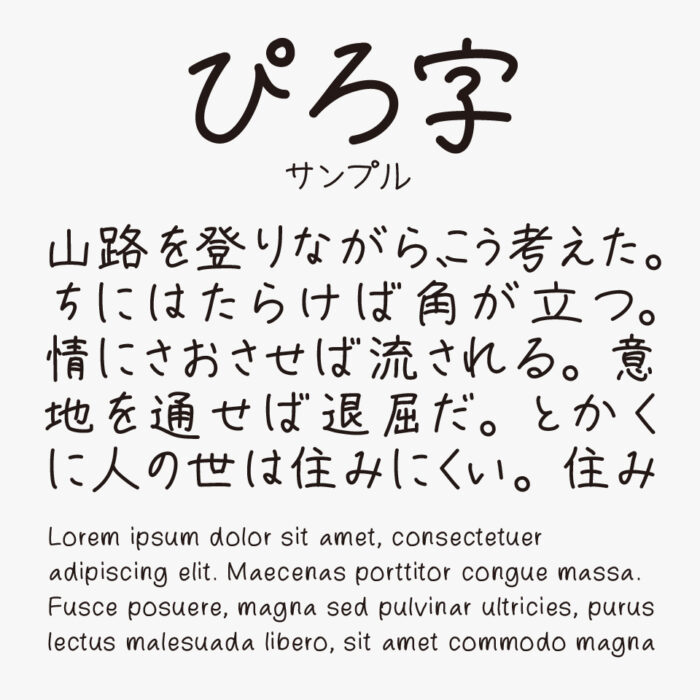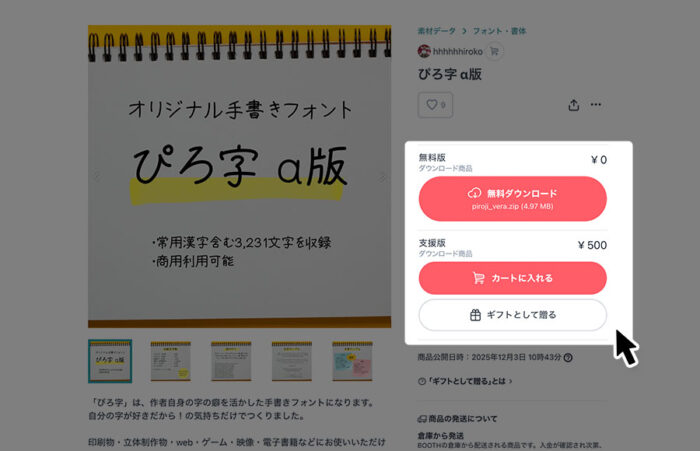
ぴろ字 α版
ぴろ字 α版は、やさしい手書き感と丸みを帯びた線が特徴の、作者はらだひろこさんの字の癖を活かした手書き風フォントです。
文字は少し丸めで、整った字ながら無垢さと安心感があり、素朴な表情をもっている手書き文字です。ナチュラルで飾らない印象を与えたいときに使いたくなる、あたたかみのあるフォントです。